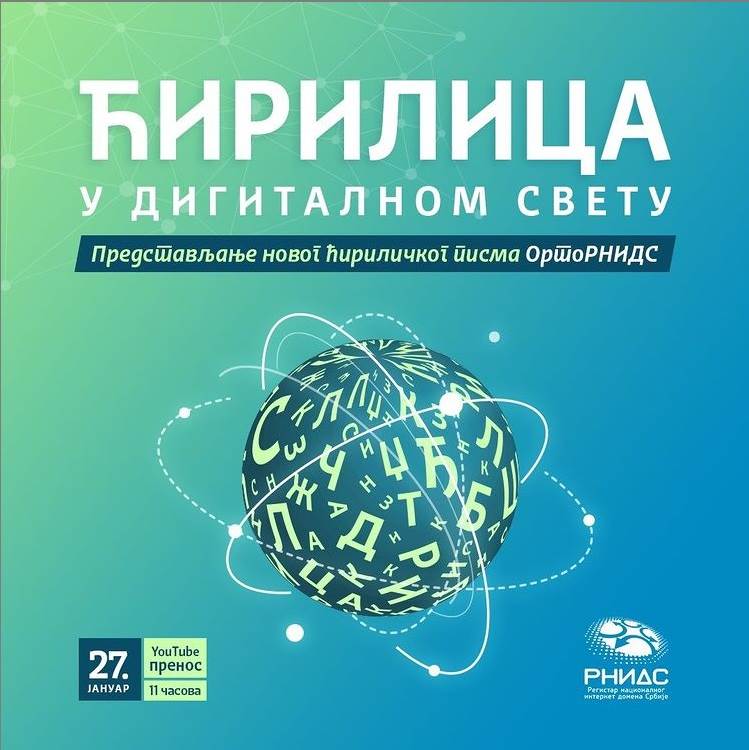
Ovo je drugo po redu ćiriličko pismo čiju je izradu RNIDS omogućio, a kreirano je kroz saradnju sa organizacijom Tipometar.
Za razliku od pisma Areal RNIDS, predstavljenog u januaru 2020. godine, slabserifnog tipografskog pisma, Orto RNIDS je sanserifno tipografsko pismo humanističkog tipa. Izvedeno je u uspravnom i kurzivnom obliku, u dve težine. Kreirano je sa idejom da se oblici slova dobro prilagode prikazu na ekranu, a podjednako dobro se ponaša i pri upotrebi u štampi.
Orto RNIDS je novo ćiriličko pismo kreirano prvenstveno za ekranski prikaz koje Fondacija Registar nacionalnog internet domena Srbije (RNIDS) poklanja korisnicima interneta, a može se preuzeti besplatno na sajtu rnids.rs.
Autorka fontova Orto RNIDS je Ana Prodanović, docent na Fakultetu promenjenih umetnosti.
Novo pismo predstavljeno je tokom onlajn skupa “Ćirilica u digitalnom svetu“, čiji snimak imate priliku da pogledate u nastavku ove vesti. Ako želite da saznate zašto je srpske ćirilice tako malo i kod nas i u svetu na internetu - pročitajte naš tekst o tome!